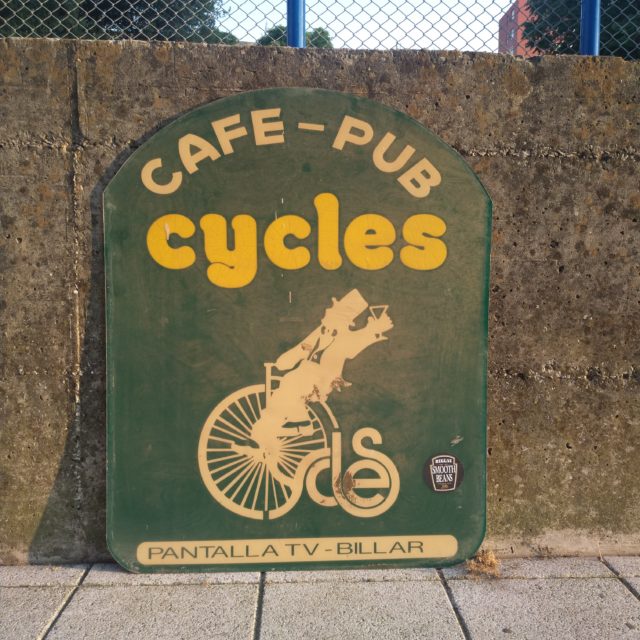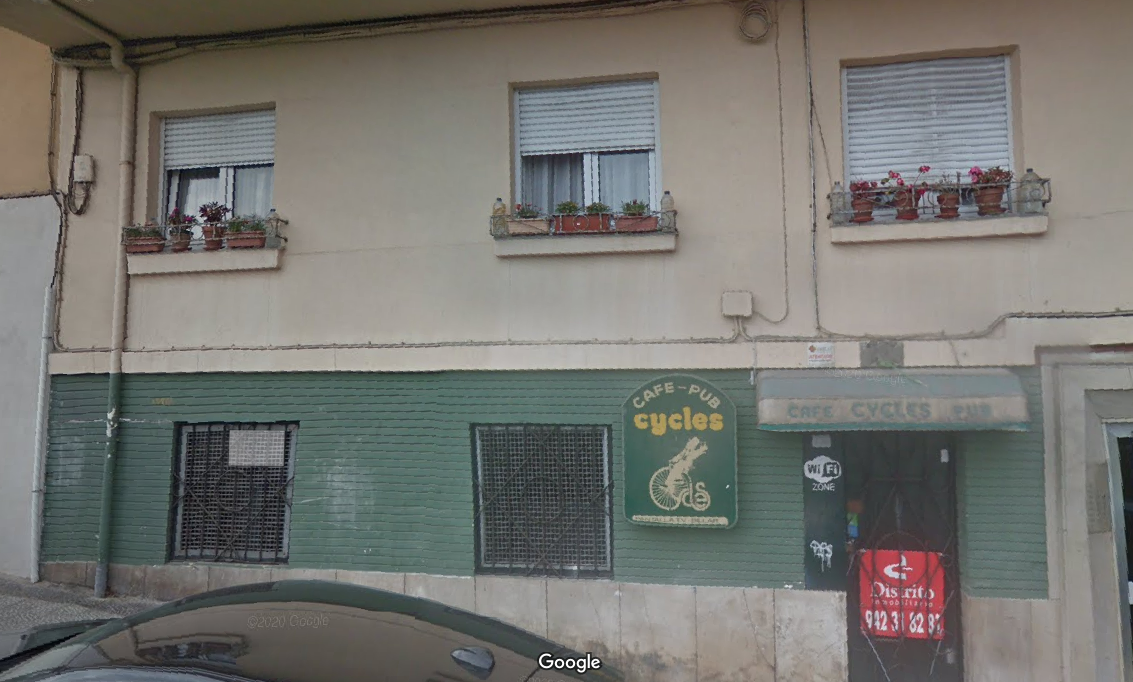
Pub Cycles
Recientemente fuimos a recoger el cartel del Pub Cycles. Lo primero queremos dar las gracias a Miguel de Refrigeracion RIVAS S.L. que fue quien lo guardo y nos avisó para recogerlo, ya que hubo obras en el local. Decir que Miguel conserva en su taller el rótulo original de la empresa de su abuelo, Eduardo Rivas, de los años 50; un rótulo realizado en madera y pintado. Una maravilla artesanal que podéis ver en el libro.
Del cartel del Cycles destaca su maravilloso isologo componiendo esa bicicleta de época y esa tipo tan redonda. Además de destacar «Pantalla TV – Billar», unos elementos característicos de ese tipo de locales de la época, donde se podía disfrutar de partidos y otro tipo de contenidos en un formato grande, poco habitual por entonces.
El «Pub Cycles» que desde los años 80 estaba ubicado en la calle Alcazar de Toledo, en la zona de la calle Alta, fue un pub que era un frecuentado por mucha gente de la zona y su historia quedará vinculada a la historia negra de la ciudad.